【網頁設計】好字型,不改嗎? 痞客邦X思源黑體 提升網頁質感~
中文字體或字型一直是網頁設計者的一大難題,當你設定網頁使用某一個好看的中文字體時當下使用自己的電腦看是正常的,但是別人的電腦不一定有安裝你設定的字型,這時候該怎麼辦呢? 這時 Google 推出的免費網路字體 – 思源黑體,絕對是你的好選擇。
當別人看你的網站時沒有你設定的字體,網站就會以新細明體(Windows 系統)或蘋方體(Mac系統)為主,於是為了讓網站有更多的字型選擇最後產生了「網路字型」的服務,不用每台電腦都安裝你設定的字體就能看到正確的字型~
新細明體
你是使用 Windows 系統嗎? 那麼你一定對新細明體這個字型很熟悉,對於從事平面設計或是網頁設計的人來說,新細明體就像它的名字一樣太細了。
有時候在放在圖片上、網頁上實在是不明顯,畢竟Windows系統已經被大家使用很久也習慣了新細明體這個內建字體,但是用在網頁上對於Kent這種長時間使用電腦的人會讓眼睛看起來很吃力。
想要使用其它字體不是不行,前提是你的電腦需要有我使用的字體,不然還是會自動以新細明體顯示,因此就出現網路字型這個解決辦法,這次就與你分享如何修改痞客邦的顯示字體吧~
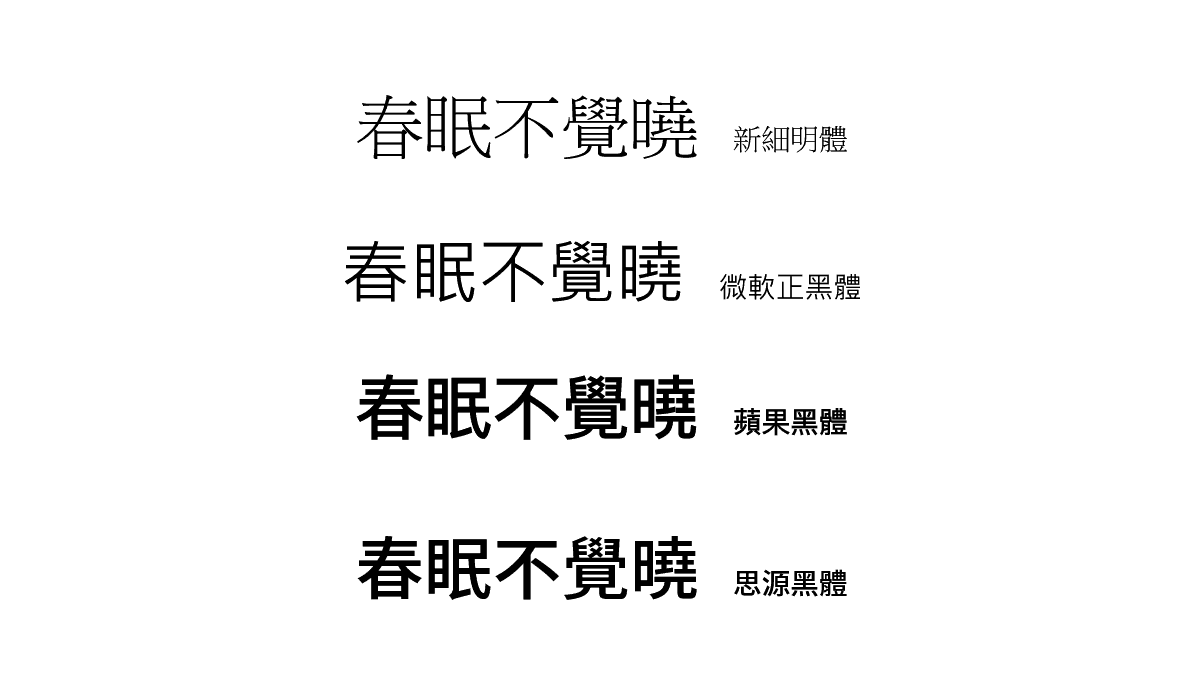
上面這幾種字型你喜歡哪一種呢?
網路字型簡介
網路字型(Web Font)主要用途在使用於網頁上的字型顯示,擺脫以往字型需安裝方能顯示的限制,使得於網頁設計上能夠不用轉圖檔,使用者一樣能夠看到特殊的字型效果。
目前在英文語系國家,網路字型的使用甚為方便,但在亞洲語系國家則限制頗多,主要的困難點在於亞洲語系國家的字數太多,導致單一字型檔的大小,動輒5~6M,甚至有達到10M以上的字型檔案。
要在瀏覽時下載整個字型檔是不現實的。網路字型機制,是依據您網頁上使用的文字,動態的產生並下載您需要的字型,所需下載的檔案大小等同於圖檔,且使用方便無須額外設定。資料來源 造九頑五
網路字型推薦
網路字型有付費及免費,付費的網路字型會依照你的訪客流量來收費,付費的部份就先不討論,這次要與你分享的是由 Google 所推出的好用中文字型,一共有思源黑體、楷體、圓體、仿宋體、 明體等五種中文字體可以使用。
目前只有思源黑體外在 Google Fonts 網站上找得到,剩下的字型因為還是測試版只在 Google Fonts Early Access 這個網站上出現過,現在已經看不到了,但是相關的檔案連結依然可以使用。
字型展示
總結
好的字型可以為你的網站加分很多,尤其實在閱讀方面會讓讀者看起來更舒服,這邊 Kent 要給你2個小提醒,上面提到Google Font 除了思源黑體外的字型都還是測試版,目前可以使用不代表著Google Font 以後不會刪除這些字體。
如果想要玩看看沒關係,正式使用還是推薦你使用正式版本的思源黑體會比較保險,第2個提醒請你一次選擇一個字型就好,載入2個以上的字型會因為字型檔案太大,瀏覽網頁的速度會變慢!!